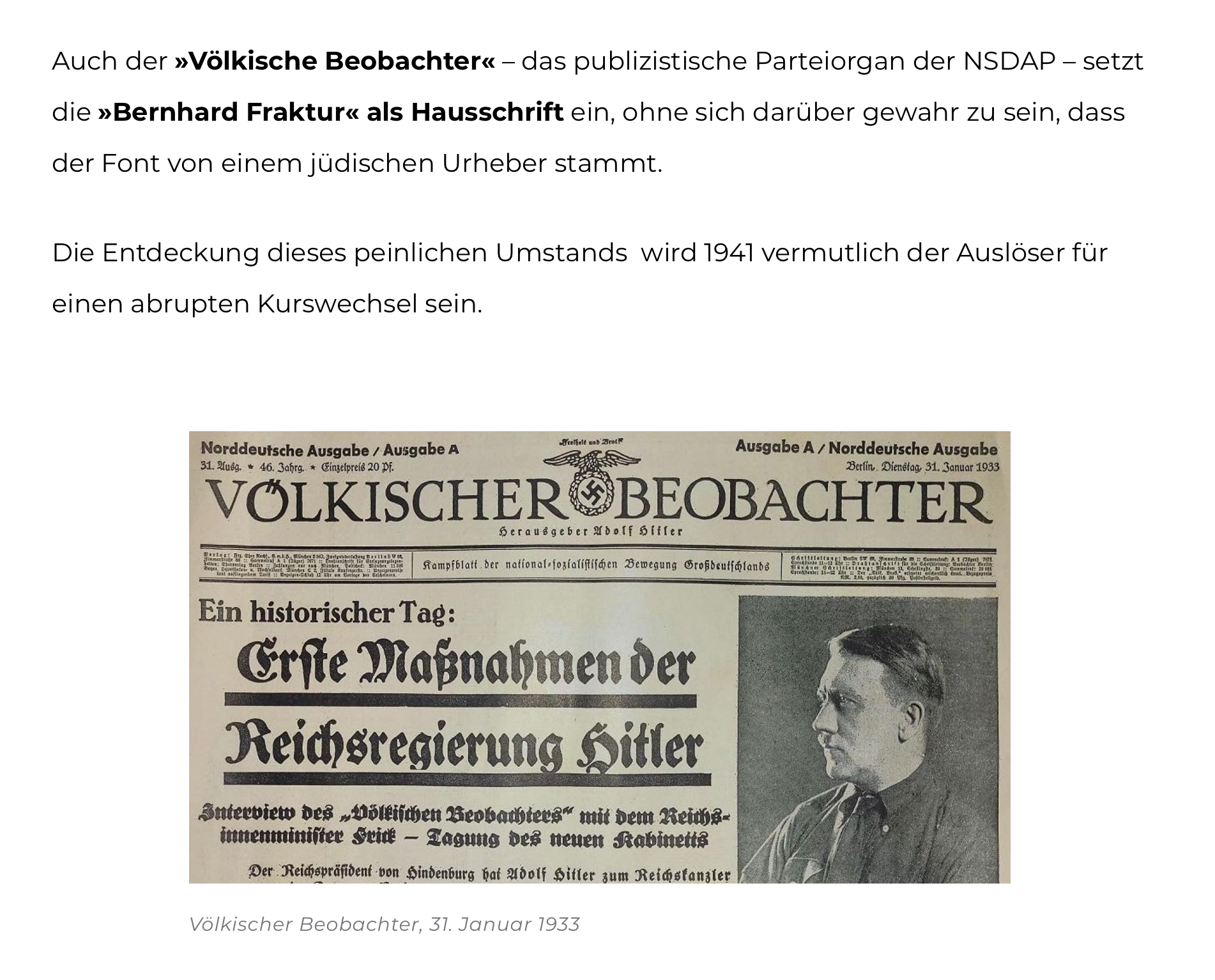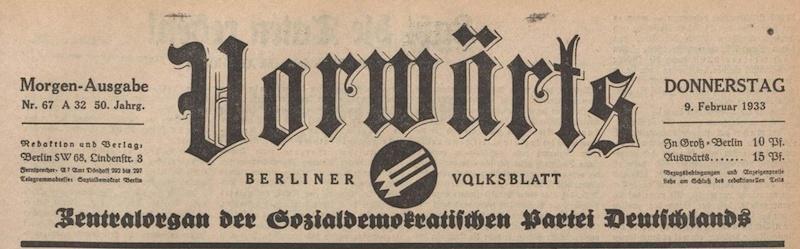
Welche Schriften im Dritten Reich und in der DDR?
Der Gedanke, eine Fraktur mit einer Grotesk zu kreuzen, war auch so zeitgeistgemäß und hätte des Nationalsozialismus nicht bedurft.
Endlich eine korrekte Antwort! Natürlich war die fette Gotisch für die Werbung als Pendant zur fetten Grotesk gedacht. Aber nicht eigens für Parteiwerbung.
Es gab keine NS-Schrift. Der Staat benutzte für seine Repräsentanz Antiqua,
die seinem sonstigen Pseudoklassizismus entsprach. Hitler selbst mokierte sich über die ewigen Rückwärtse, wie er sie nannte, mit ihrer Schnörkelschrift.
Für das ominöse immer wieder kolportierte Wort Schaftstiefelgrotesk habe ich noch keinen Beleg gefunden. Vielleicht kann jemand helfen?
P.S. Wer hat den Schriften damals eigentlich üblicherweise den Namen gegeben? Die Gießerei oder Schriftgestalter?
Soviel ich weiß, die Marketingabteilung der Gießerei.
Ich habe in den letzten Tagen die Wikipedia-Artikel "Antiqua-Fraktur-Streit" und "Gebrochene Grotesk" kräftig überarbeitet und zahlreiche Quellen ergänzt, die die meisten historischen Fragen beantworten müssten.
Es gab keine NS-Schrift.
Stimmt. Ein Blick auf die Postersammlung des Calvin College zeigt ein beliebiges Sammelsurium an Schriften:
Für das ominöse immer wieder kolportierte Wort Schaftstiefelgrotesk habe ich noch keinen Beleg gefunden. Vielleicht kann jemand helfen?
1960 schrieb Jan Tschichold über die "in Schaftstiefeln marschierende Kochschrift“. Ich könnte mir aber gut vorstellen, dass das Bild schon in den 30ern verwendet wurde. Bin noch auf der Suche nach einer besseren Quelle.
Ich verbinde mit dem NS ab September 1939 eher eine Schreibmaschinenschrift, denn eine Gebrochene, wenn ich einen Schriftbezug als Klischee herstellen müsste. … Holocaust versus Kraft durch Freude. Auch aufgrund der anteiligen Berichterstattung in den Medien, dem Schulunterricht.
Ja! Ich würde sogar noch etwas weiter differenzieren:
• Eine klassische Normal-Fraktur als Klischee für die deutschtümelnde Fraktion, die das "Dritte" Reich als Fortsetzung von Zweitem Reich (Kaiserreich) und Ersten Reich (Heiliges Römisches Reich) erträumte,[/*:m:3dfhnh2n]
• eine leicht verschmierte mechanische Schreibmaschinenschrift als Klischee für den gnadenlosen, perfekt durchorganisierten, gleichgeschalteten Bürokratenapparat,[/*:m:3dfhnh2n]
• für Hitler als "Kaiser und Gott" (im antik-römischen Sinne) eine glatte Antiqua, vielleicht sogar was serifenloses, modernes, maschinelles, wie auf den Wahlplakaten von 1932,[/*:m:3dfhnh2n]
• für Soldaten, Krieg, Bomben, Schlachten eine fette Gebrochene Grotesk (wie sie 1936 für Uniformen und Schiffsnamen und bis Kriegsende für Kriegspropaganda genommen wurden)[/*:m:3dfhnh2n]
• Nationalsozialismus als religionsähnliches Heilsversprechen für die Massen symbolisiert das Hakenkreuz, am besten mit Lichtstrahlen à la Parteitag oder Eichenlaub(?)-Kranz oder Adler (ist aber aus juristischen Gründen mit Vorsicht anzugehen, wenn überhaupt)[/*:m:3dfhnh2n]
• Antisemitische Hetze und Massenmorde sind mit einem Judenstern und der darin verwendeten pseudo-hebräischen Schrift verbunden[/*:m:3dfhnh2n]
Das wäre auch eine Antwort auf die Ausgangsfrage nach "Schriften im Dritten Reich". :-)
die wurden verboten, als sie merkten, dass sie jüdischen ursprung haben
Halt, aufgepasst! So kann man auch einen Wiki-Eintrag falsch lesen. Niemand hat „gemerkt“, dass die Fraktur jüdischen Ursprungs war, denn das war sie natürlich nicht. Sondern die Nazis haben die Schrift diffamieren wollen, die ihnen 1941 unpraktisch erschien. Und diffamiert war alles, was jüdischen Ursprungs war in Kultur und Wissenschaft. Also wurden die gebrochenen Schriften kurzerhand zur „Schwabacher Judenletter“ erklärt und damit nicht mehr für einen „ordentlichen“ Deutschen zu verwenden.
Für das ominöse immer wieder kolportierte Wort Schaftstiefelgrotesk habe ich noch keinen Beleg gefunden. Vielleicht kann jemand helfen?
1960 schrieb Jan Tschichold über die "in Schaftstiefeln marschierende Kochschrift“. Ich könnte mir aber gut vorstellen, dass das Bild schon in den 30ern verwendet wurde. Bin noch auf der Suche nach einer besseren Quelle.
Ich kenne aus der Literatur den Begriff „Schlichte Gotisch“.
»Gebrochene Grotesk« scheint mir für eine sachliche Klassifizierung am nützlichsten
Nö, das würde sich ja auch auf eine Grotesk beziehen, die mit Formelementen, die aus den gebrochenen Schriften stammen, "angereichert" wird. Schliche Gotisch finde ich recht aussagekräftig.
»Gebrochene Grotesk« scheint mir für eine sachliche Klassifizierung am nützlichsten: http://de.wikipedia.org/wiki/Schlichte_Gotisch
Danke! Als Hauptautor des Wikipedia-Artikels "Gebrochene Grotesk" freue ich mich über die Bestätigung. :-)
Nö, das würde sich ja auch auf eine Grotesk beziehen, die mit Formelementen, die aus den gebrochenen Schriften stammen, "angereichert" wird. Schliche Gotisch finde ich recht aussagekräftig.
Selbst ausdrücklich linke Drucksachen (wie Zeitungen)
Eben. (what the man says …)
Nachtrag: Auch die »Lieder« des Arbeiterdichters Heinrich Kämpchen erschienen beispielsweise teils in Fraktur gesetzt.